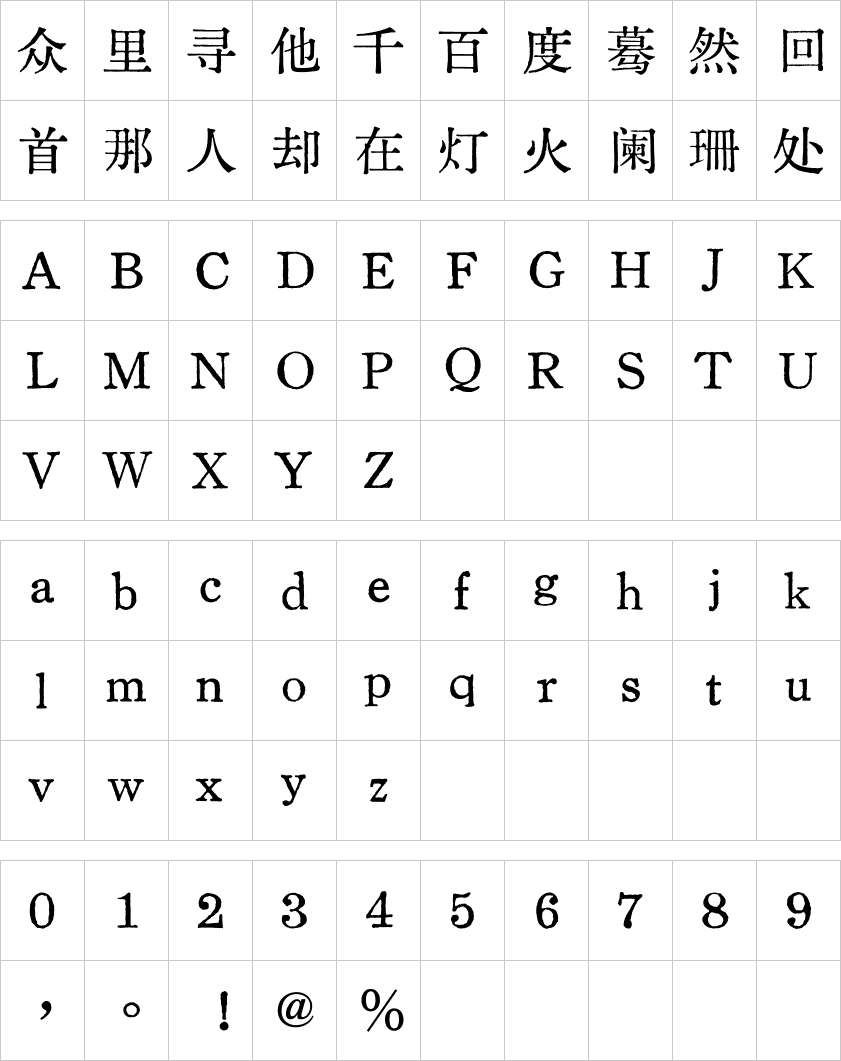
京華老宋体
2022年年 6 月初,我(这里的我指字体作者)发了一篇《寻找老宋体:试着探索一下 61-1 体》。要说为什么会去搞这番探索,正是因为那时我在做这款扫描字体。当时我为了收集字样,遍查孔网旧书,寻觅老 61-1 体的印刷品。对 61-1 这个字体,越看越熟悉,慢慢发现了一些规律和特点,就稍微记录整理了一下,作为一个阶段性总结,汇集成了那篇东西。在那之后,我也继续在收集字样。时隔一年多,终于,我觉得这个字体弄得差不多可以用了,是时候该丢出来了。
惯例之发布之前先讲讲故事,要说扫描铅字的字体,之前我已经发过两个了,这次怎么又做了一个呢?嘛,首先,这几个字体侧重点还是不一样
【汇文明朝体】当时做的想法是弄一个复原早期铅字印刷品风格的字体。那个时候我对这些字体具体的来由、故事毫不了解,所以就只顾胡乱收集字样。管他什么字号,什么来历,只要是当时存在的老宋体,都往里面填。整个就是一个不成体系的大杂烩。并且那时的很多铅字字模破烂,加上纸张粗糙,印刷时油墨不均,再由我一扫描,一转曲线,那真是,要多狗啃有多狗啃。但你还甭说,效果是真达到了,弄出来的字还真挺有当时印刷品内味儿。
而【筑地五号】只是在做汇文明朝的过程中想要偷懒,妄图把一个完整的明朝体见本整个收录进去,结果发现风格不合适只好单独分离出来,另成一个字体而来的。这个倒是成体系了,但是收字不多,没法正常用。
于是我一直想弄套真正成体系,并且尽量不那么狗啃的铅字扫描字体出来。